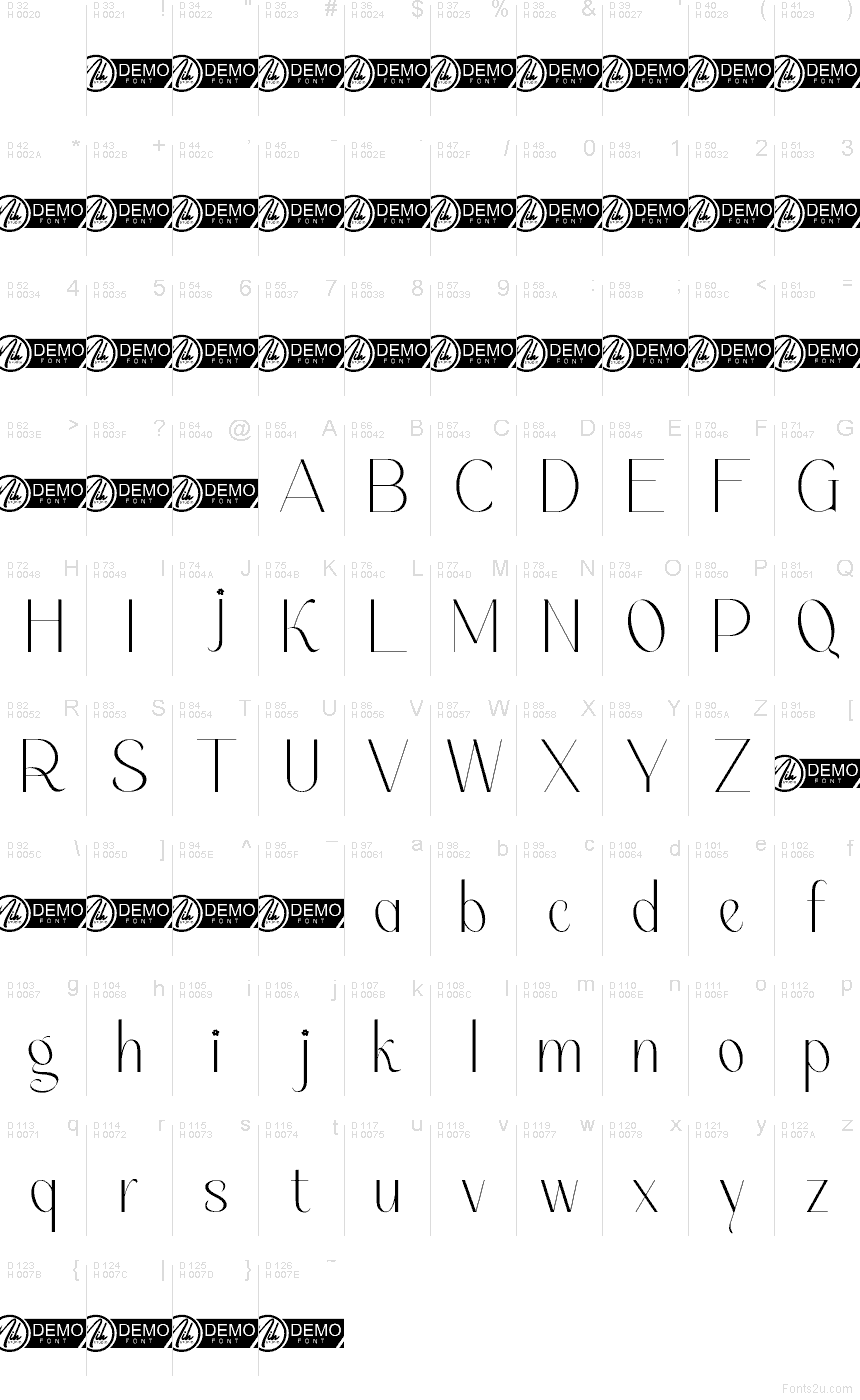
Flora Sentani من NoahType هو خط عرض (display font) مجاني بنمط ريترو، يتميز بصورة ظلية شاهقة ومتزنة مع تباين لافت بين المنحنيات الدقيقة والضربات الرأسية الأكثر ثباتاً. يمنح هذا التباين الحروف حضوراً أنيقاً يشبه تصاميم الملصقات، مع قدر كافٍ من الرصانة ليظل مزخرفاً دون أن يكون متكلفاً.
سواء كان الأمر يتعلق بالتغليف، أو الهوية البصرية للمتاجر، أو قوائم المقاهي، أو عناوين الفعاليات، أو الترويسات التحريرية، فإن Flora Sentani هو الخيار الأمثل حيث تضفي لمسة من الوقار لتحديد النبرة المناسبة. تمنح الأشكال الممدودة والمنحنيات الانسيابية للنصوص القصيرة دوراً متميزاً، خاصة في التنسيقات التي تسعى إلى طابع كلاسيكي (vintage) دون الاعتماد على زخارف واضحة.